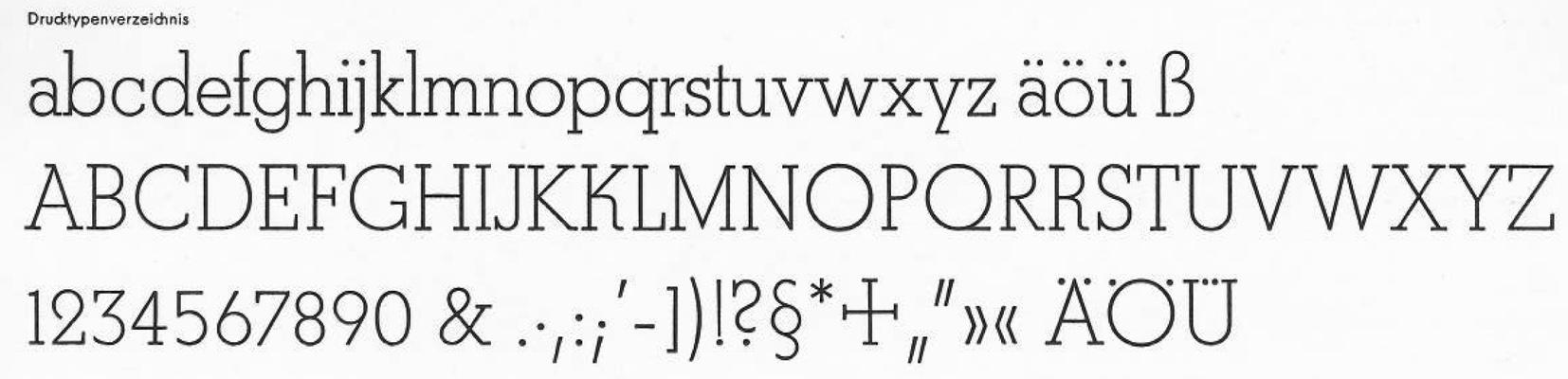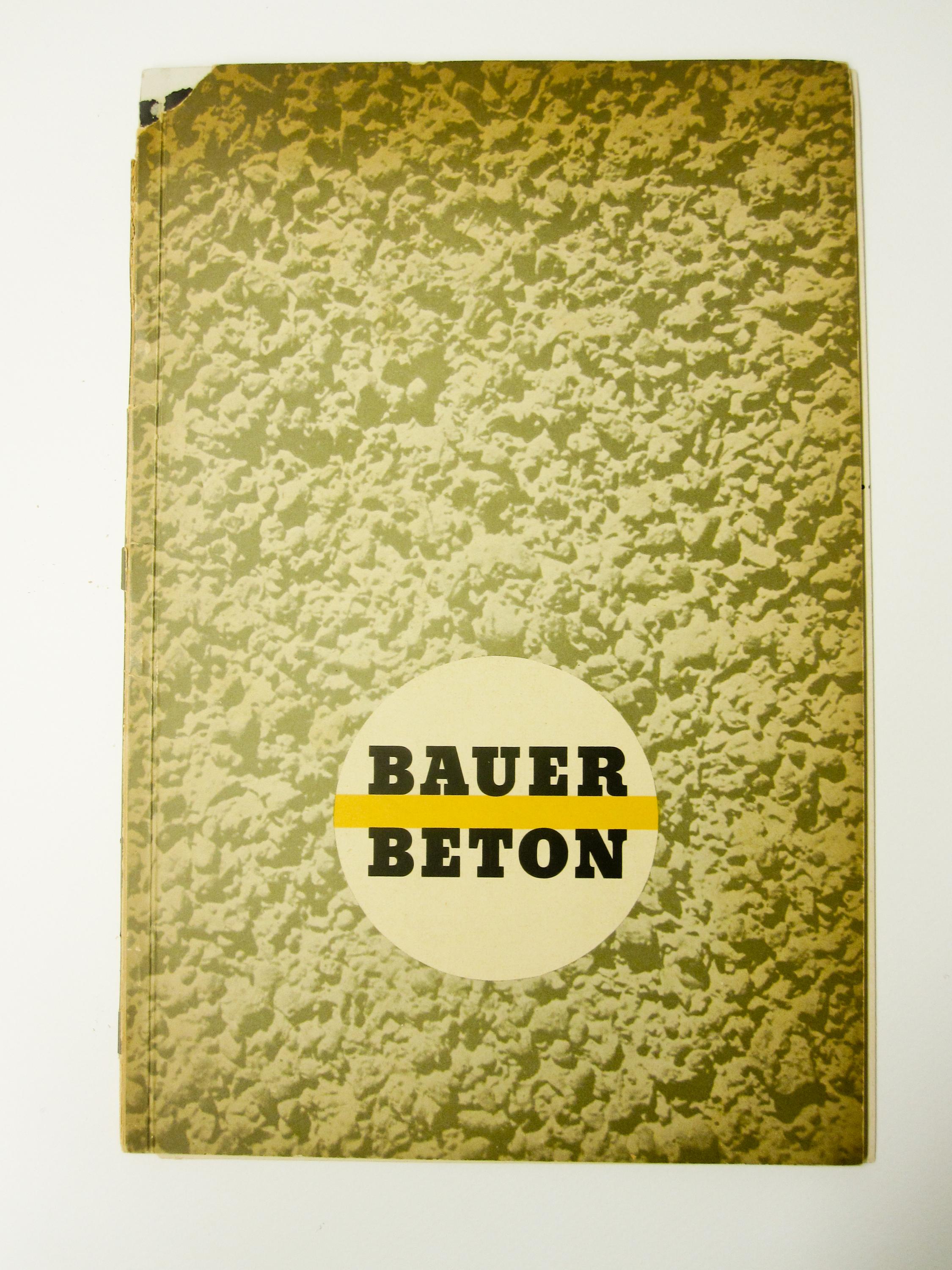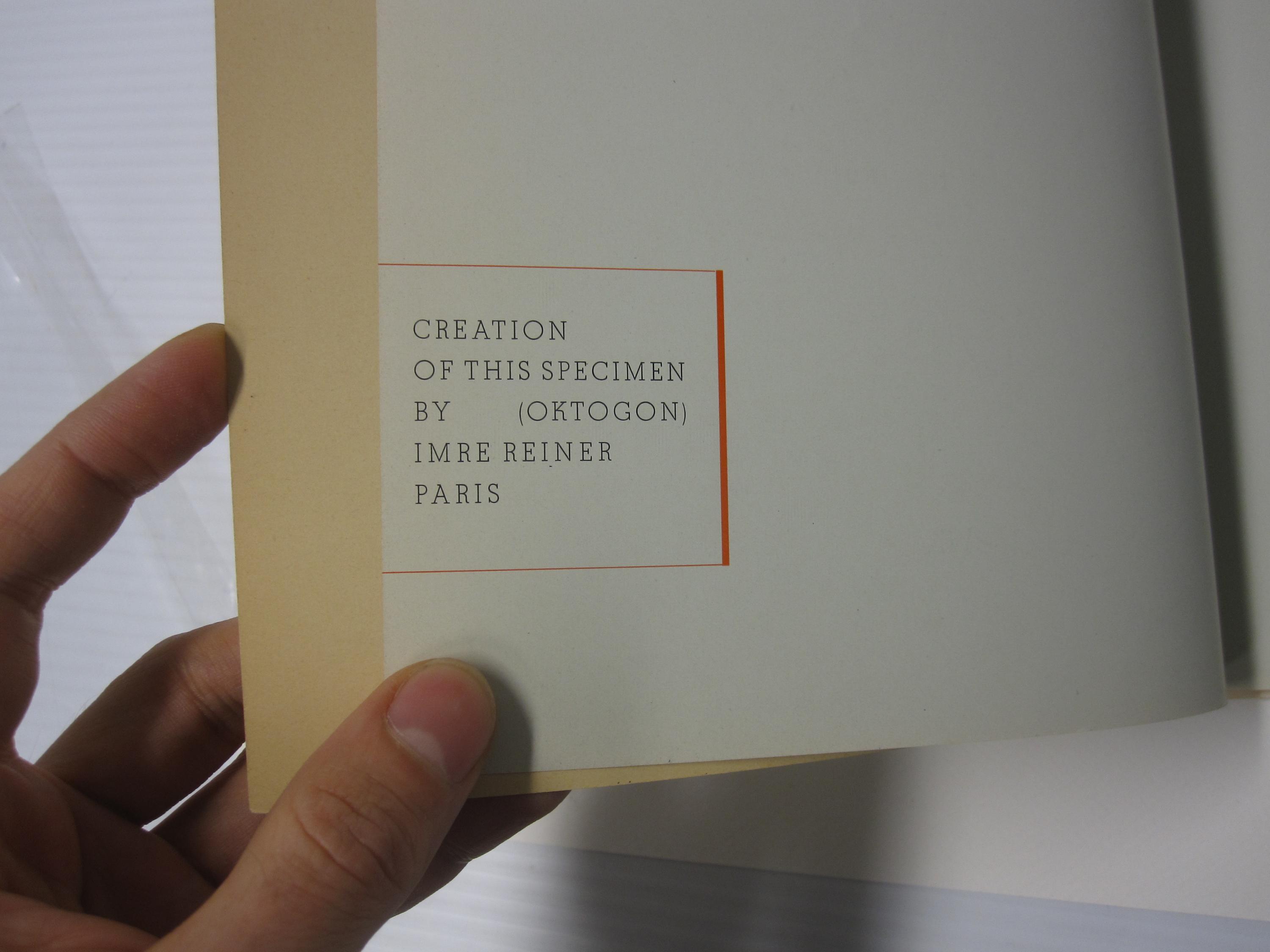
Bauer Beton von Heinrich Jost
Ich habe dieses Bild entdeckt, auf dem wohl die Bauer Beton abgebildet ist. Allerdings ist beispielsweise das "K" recht eigenwillig gestaltet. Diese Form habe ich bei keiner heute erhältlichen Beton-Version finden können. Weiß jemand hierzu etwas? Gibt es eine ursprüngliche Fassung der Beton, die später nicht digitalisiert oder für den Fotosatz bearbeitet wurde? Oder ist hier die Schrift "Oktogon" abgebildet? Die wäre mir aber dann völlig unbekannt …
Es gab eine Variante zum K.Beton mager.jpg.
Danke, Erwin! Genau diese Variante habe ich gemeint. Weisst Du zufällig, ob sie mal digitalisiert wurde bzw. ob sie erhältlich ist?
Bei der Beton kenne ich auch keinen Font der die Alternativform des „K“ beinhaltet.
Jedoch bei der „Hunter“, die ähnlich der Beton ist, wurde ziemlich genau diese Form aufgegriffen.
Leider habe es viele Alternativformen nicht ins digitale Zeitalter geschafft. Ich bin immer wieder erstaunt wenn ich mir alte Muster anschaue. So gab es Beispielsweise für die Gill  kleinere Versalien für den deutschen Satz die sich harmonischer ins Satzbild eingliederten.